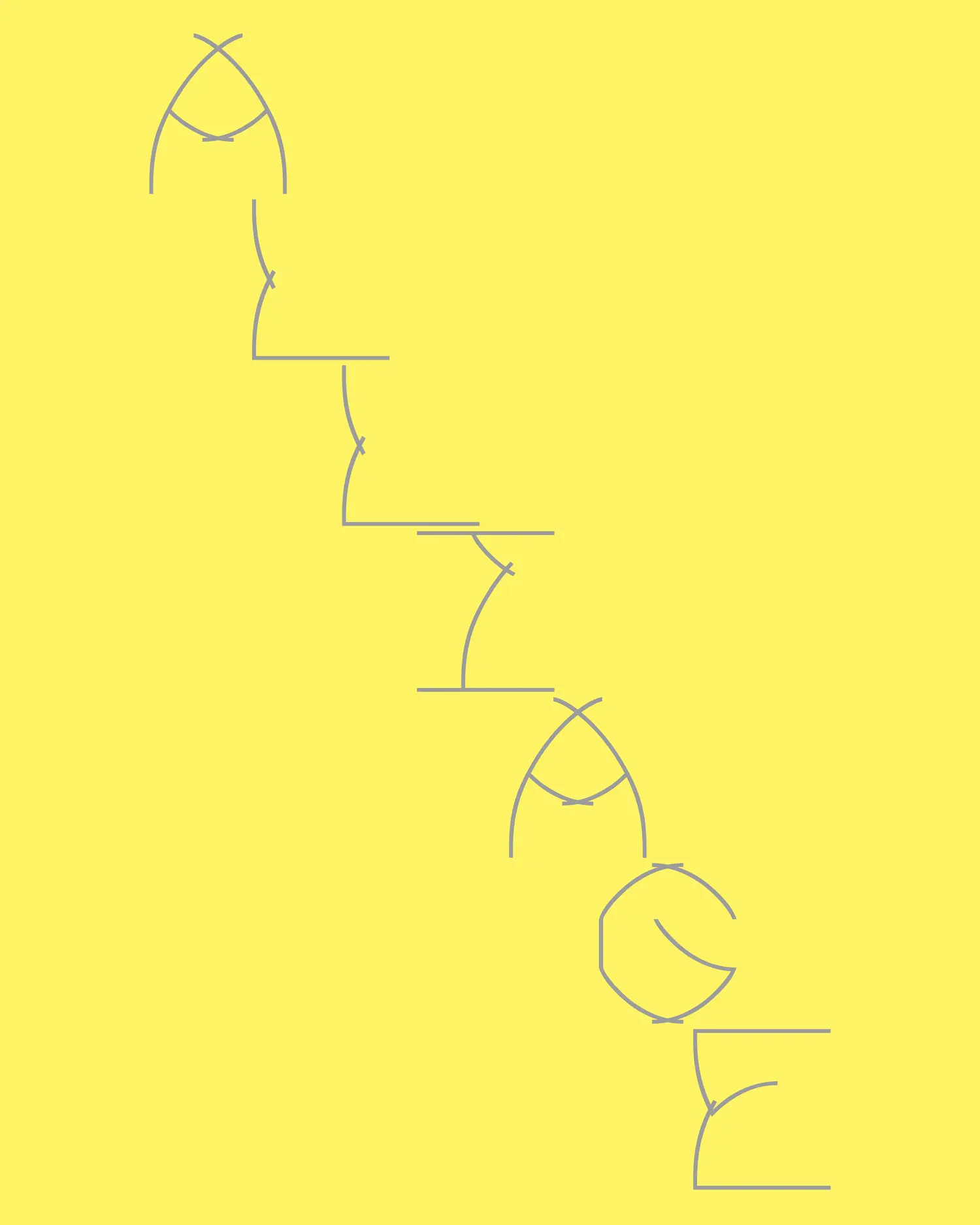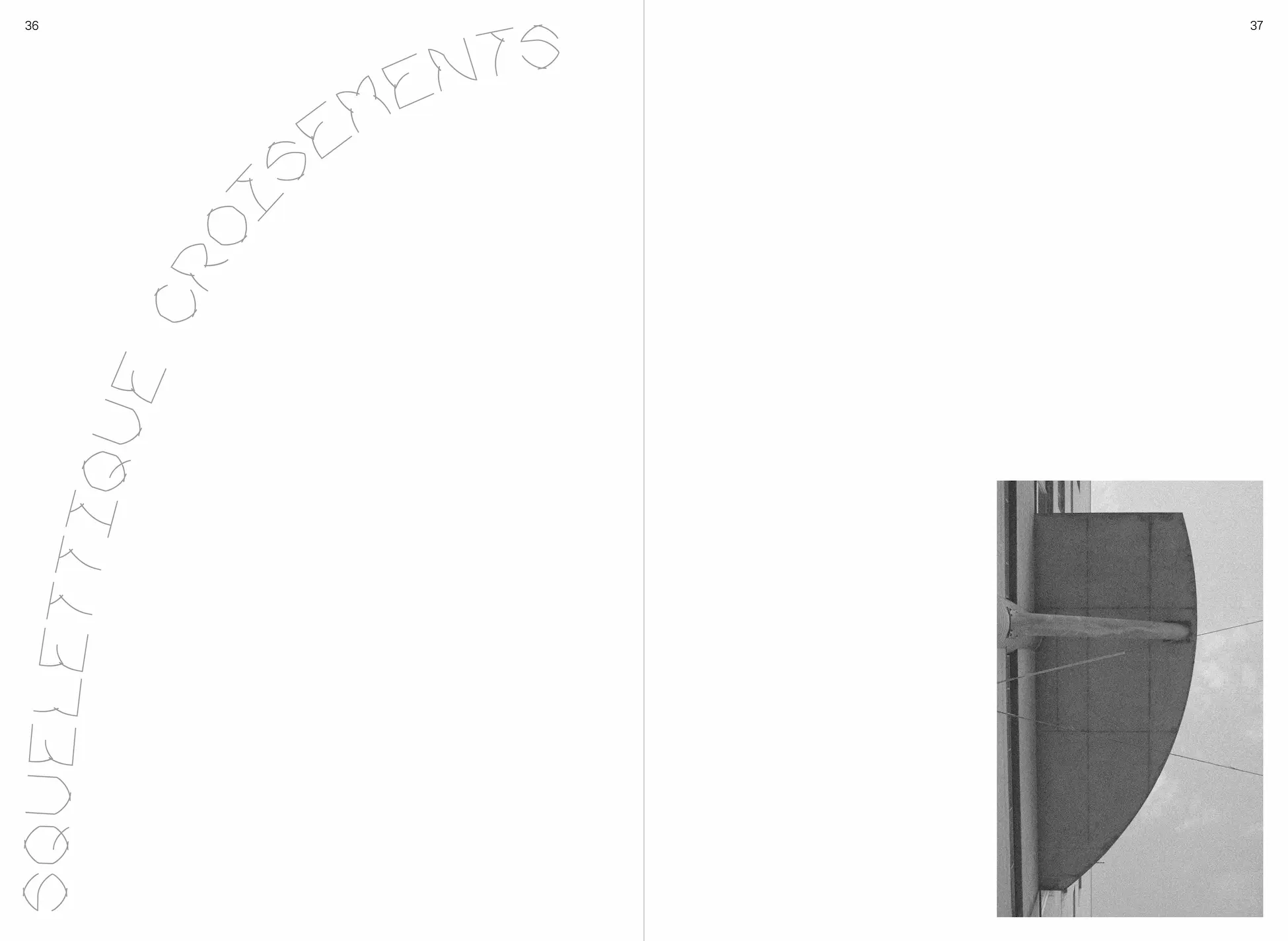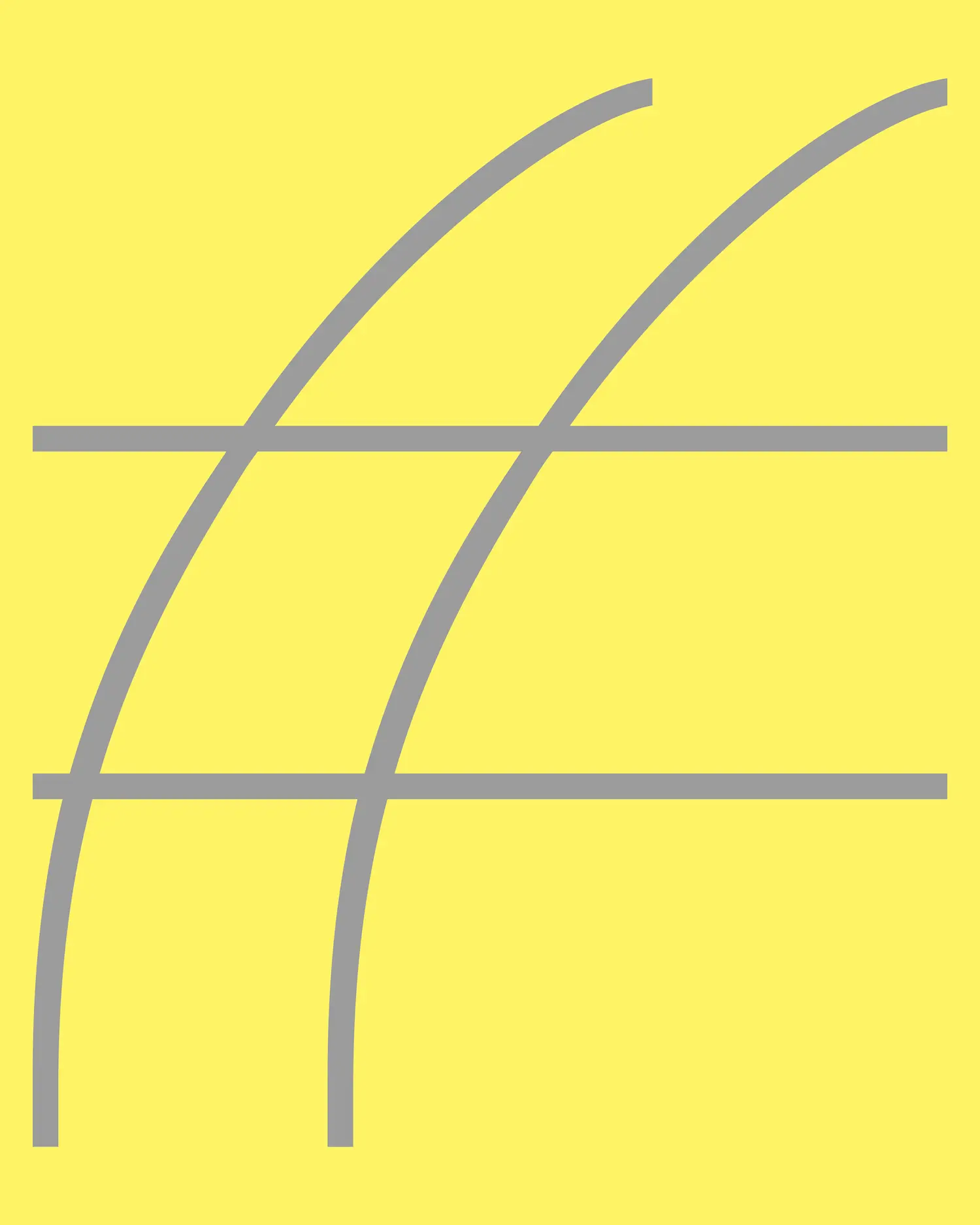
Alliage est une police de caractères conçue pour mettre en dialogue différentes pratiques du design. Elle a été développée pour l’identité visuelle de l’événement Design International à l’École de design de l’UQAM. Depuis 1982, cet événement accueille des invité·e·s internationaux issus de divers champs du design, principalement du design graphique et du design de l’environnement. Conférences et ateliers offrent aux étudiant·e·s un espace privilégié pour explorer diverses approches de la pratique du design. L’intention principale derrière cette police était d’allier ces disciplines distinctes tout en exprimant l’essence même de l’événement : la rencontre, le partage et la collaboration. Cette jonction passait naturellement par le lieu qui les accueille, un espace où ces pratiques coexistent et se rencontrent au quotidien. Le Pavillon de design s’est ainsi imposé comme point de départ. Ses grandes fenêtres emblématiques à neuf carreaux rectangulaires, ses arcs multiples et plusieurs éléments de sa structure intérieure ont servi à générer une grille modulaire qui a guidé la conception de la police ainsi que les formes qui composent chaque caractère. La création des glyphes s’est faite par combinaisons successives de ces formes : superpositions, croisements, chevauchements et ajustements, jusqu’à obtenir un ensemble cohérent. Le nom Alliage reflète cette fusion : des éléments distincts qui se rencontrent pour créer quelque chose de nouveau, à l’image même du processus de création qui s’est développé de manière collaborative entre les designers. Bien que fondée sur des formes architecturales stables, la police adopte une apparence expérimentale et élancée, où des détails singuliers se révèlent à mesure que la structure se déploie.